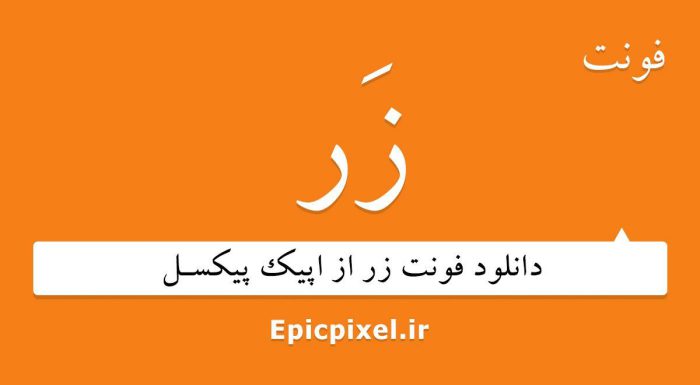
فونت زر درخشش زیبایی در قلم فارسی
فونت زر انتخابی عالی برای طراحی های خلاقانه و خوانایی آسان
فونت زر، یکی از فونت های فارسی پرکاربرد و محبوب است که به دلیل زیبایی، خوانایی و قابلیت تطبیق پذیری بالای آن، در طراحی انواع مختلفی از محتوا، از جمله عناوین، متن های طولانی و تبلیغات، مورد استفاده قرار می گیرد. این فونت با شکل کشیده و منحنی حروف خود، علاوه بر زیبایی بصری، خوانایی بالایی نیز دارد و باعث می شود متن نوشته شده روان و راحت خوانده شود.
ویژگی های فونت زر
فونت زر ویژگی های منحصر به فردی دارد که آن را از سایر فونت های فارسی متمایز می کند:
طراحی مدرن و زیبا: فونت زر دارای طراحی مدرن و زیبا است که آن را برای استفاده در انواع مختلف طراحی، از جمله عناوین، متن های طولانی و تبلیغات، مناسب می کند.
خوانایی آسان: فونت زر دارای خوانایی بالایی است و باعث می شود متن نوشته شده روان و راحت خوانده شود. این فونت به ویژه برای استفاده در متن های طولانی بسیار مناسب است.
قابلیت تطبیق پذیری بالا: فونت زر با انواع مختلفی از سبک ها و طرح ها مطابقت دارد و می تواند در طراحی انواع مختلفی از محتوا، از جمله عناوین، متن های طولانی و تبلیغات، مورد استفاده قرار گیرد.
کاربردهای فونت زر
فونت زر کاربردهای گسترده ای در طراحی و چاپ دارد، از جمله:
طراحی عناوین: فونت زر به دلیل زیبایی و خوانایی بالای آن، برای طراحی عناوین بسیار مناسب است. این فونت می تواند در طراحی عناوین وب سایت ها، مجلات، کتاب ها و سایر موارد استفاده شود.
طراحی متن های طولانی: فونت زر برای طراحی متن های طولانی نیز بسیار مناسب است. این فونت باعث می شود متن نوشته شده روان و راحت خوانده شود و از چشم خواننده خسته نشود.
طراحی تبلیغات: فونت زر به دلیل خوانایی بالای آن و قابلیت تطبیق پذیری بالای آن، برای طراحی تبلیغات بسیار مناسب است. این فونت می تواند در طراحی تبلیغات چاپی، تبلیغات آنلاین و سایر موارد استفاده شود.
نکات استفاده از فونت زر
برای استفاده بهینه از فونت زر، به نکات زیر توجه کنید:
فونت زر را با فونت های دیگر ترکیب کنید: فونت زر را می توان با فونت های دیگر ترکیب کرد تا ظاهری جذاب و یکپارچه ایجاد شود.
اندازه فونت را به درستی تنظیم کنید: اندازه فونت زر را به اندازه ای تنظیم کنید که خوانا باشد.
دانلودفونت زر را در محیط مناسب استفاده کنید: فونت زر را در محیط مناسب استفاده کنید. این فونت برای استفاده در محیط های رسمی و غیر رسمی مناسب است.
نتیجه گیری
فونت زر یکی از فونت های فارسی پرکاربرد و محبوب است که به دلیل زیبایی، خوانایی و قابلیت تطبیق پذیری بالای آن، در طراحی انواع مختلفی از محتوا، از جمله عناوین، متن های طولانی و تبلیغات، مورد استفاده قرار می گیرد. اگر به دنبال فونت فارسی مدرنی هستید که خوانا و زیبا باشد، فونت زر انتخابی عالی برای شماست.